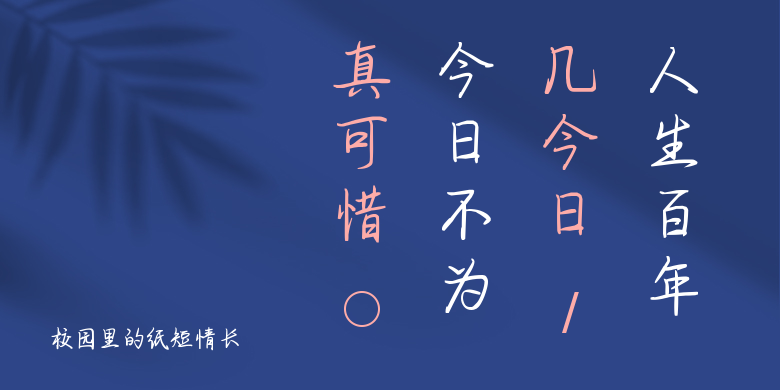
校园里的纸短情长
校园里的纸短情长,这款字体结构工整、笔画清晰,兼顾美观与易读性,适用于标题、正文、海报、包装、LOGO 等多种场景。字形优雅稳定,风格百搭耐看,适配日常排版与创意设计,让文字呈现更舒适、更具质感。校园里的纸短情长一笔一画,皆是细节,以均衡的比例、流畅的线条打造舒适视觉体验,字形端正大气,风格简约现代。无论是商业设计、品牌宣传还是日常排版,都能轻松驾驭,让文字更有格调与力量。校园里的纸短情长字体下载。